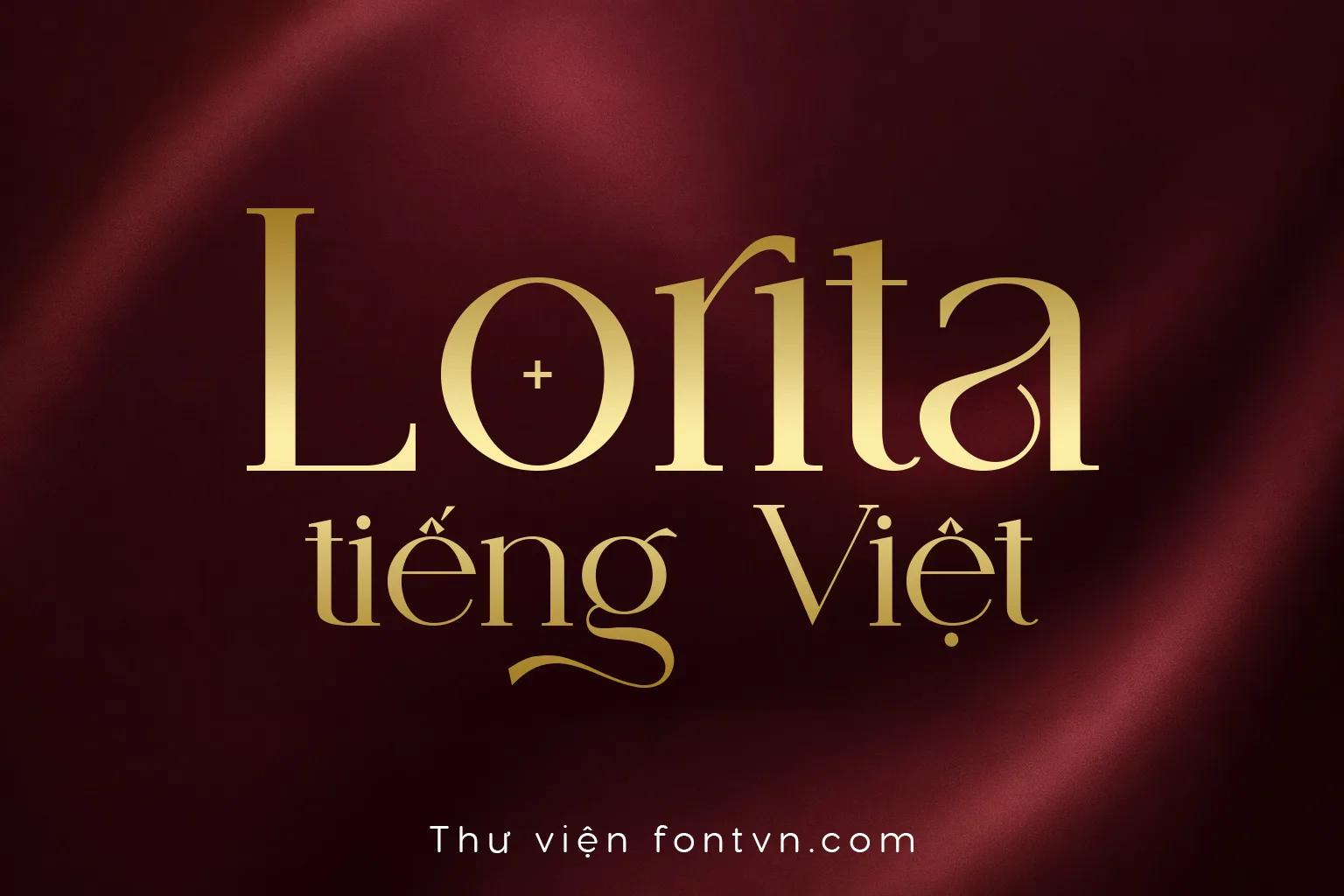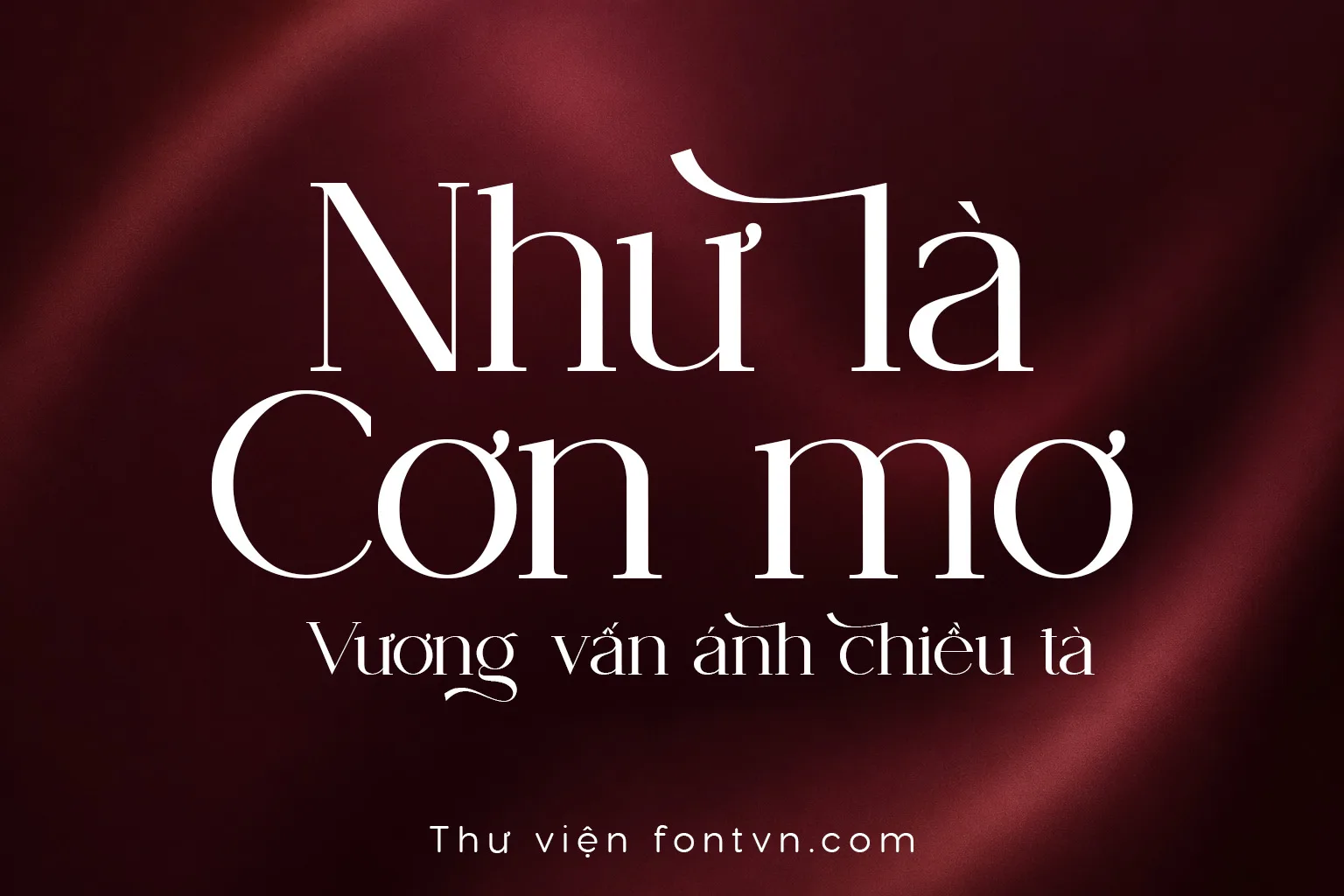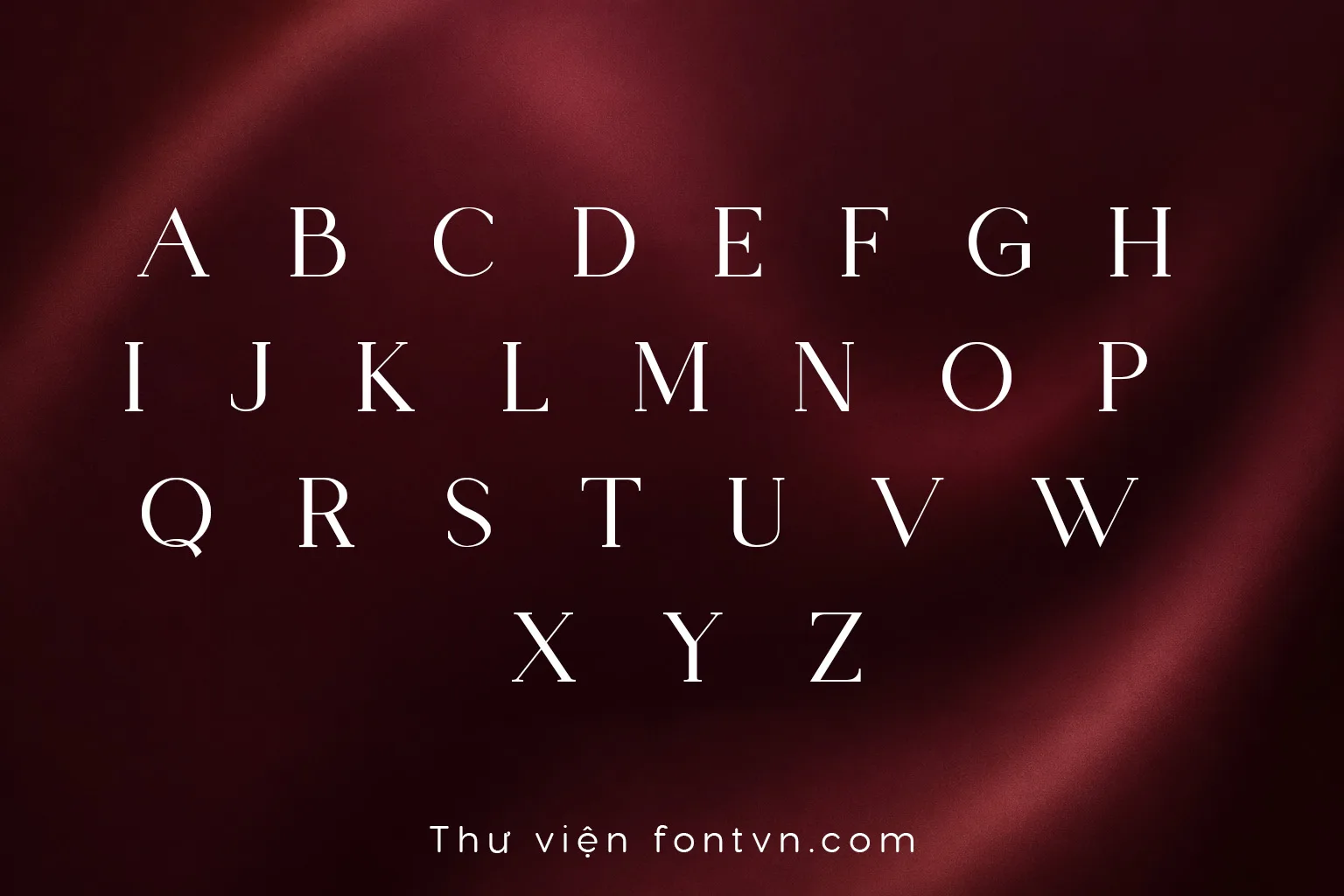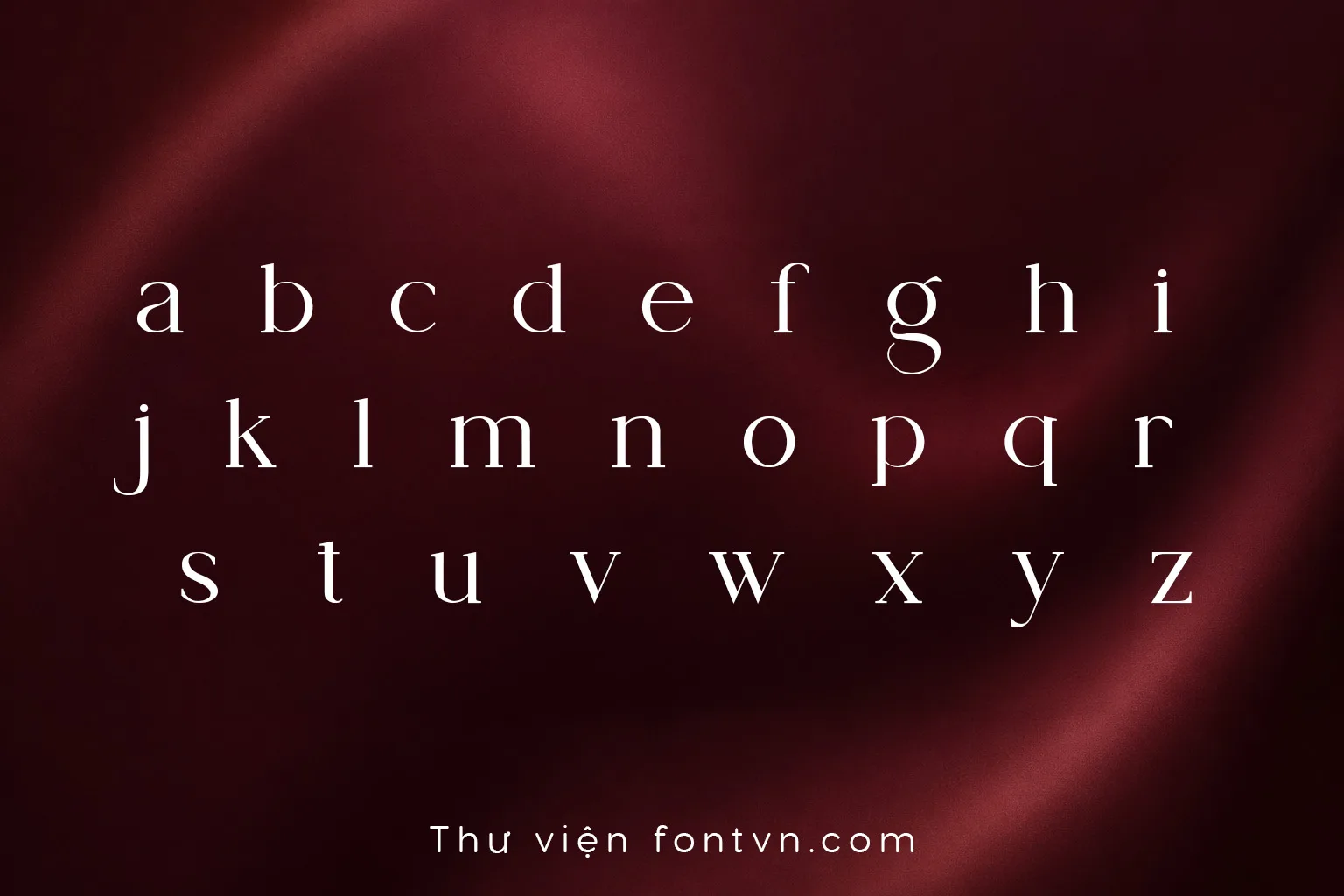
DVN Lorita tiếng Việt – Font Serif Thanh Lịch Mang Hơi hướng Boutique Hiện Đại
DVN Lorita là kiểu chữ serif cao cấp nổi bật với cấu trúc thanh mảnh, độ tương phản nét cao cùng những đường cong mềm mại đầy nghệ thuật. Font mang phong cách editorial hiện đại pha chút luxury boutique, đặc biệt ấn tượng ở các ký tự có chân mảnh kéo dài và chi tiết bo cong tinh tế tạo cảm giác sang trọng, nữ tính nhưng vẫn tối giản. Bộ font hỗ trợ tiếng Việt hoàn chỉnh, giúp giữ được vẻ đẹp nguyên bản khi ứng dụng trong các thiết kế branding, thời trang, mỹ phẩm hay social media cao cấp.
DVN Lorita phù hợp cho logo thương hiệu, tiêu đề tạp chí, banner thời trang, bao bì sản phẩm, lookbook hoặc các layout mang phong cách aesthetic và premium. Khi kết hợp với tone màu trung tính hoặc bố cục tối giản, font tạo nên cảm giác thanh lịch và đắt giá rất đặc trưng của các thương hiệu boutique hiện đại. Đây là lựa chọn lý tưởng cho designer đang tìm kiếm một kiểu serif nghệ thuật có chiều sâu thị giác và khả năng tạo điểm nhấn mạnh trong thiết kế.